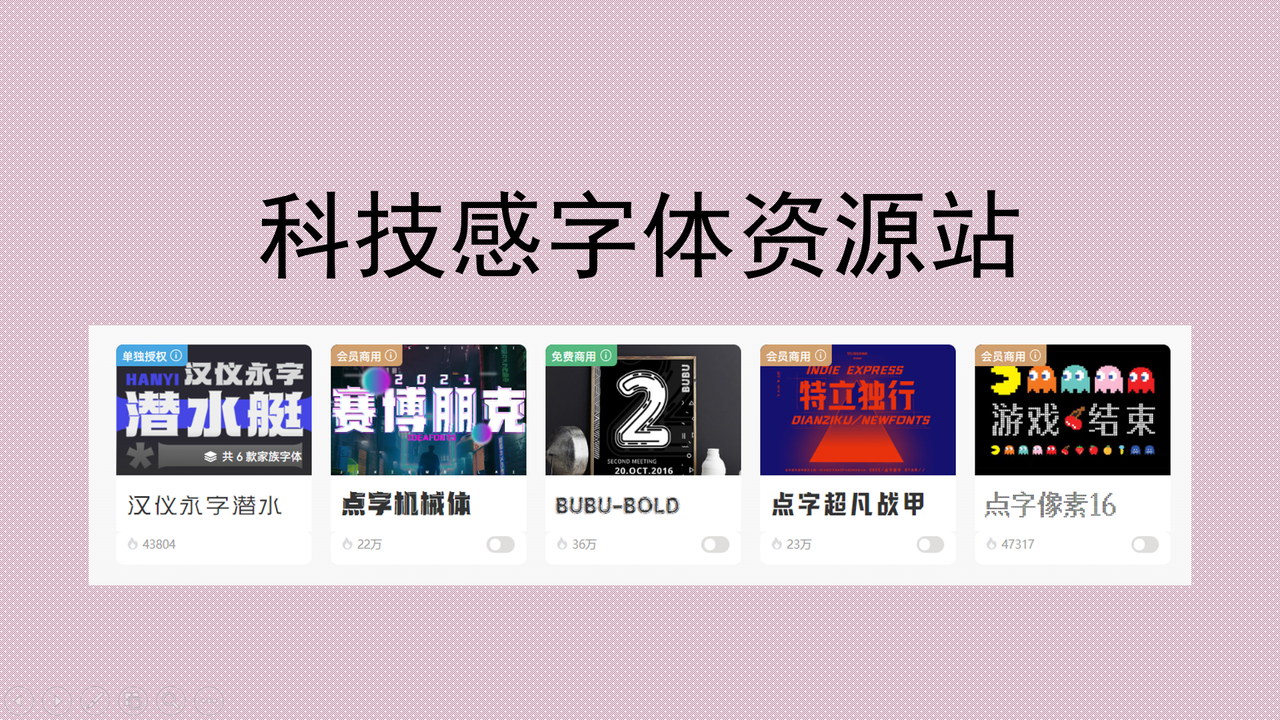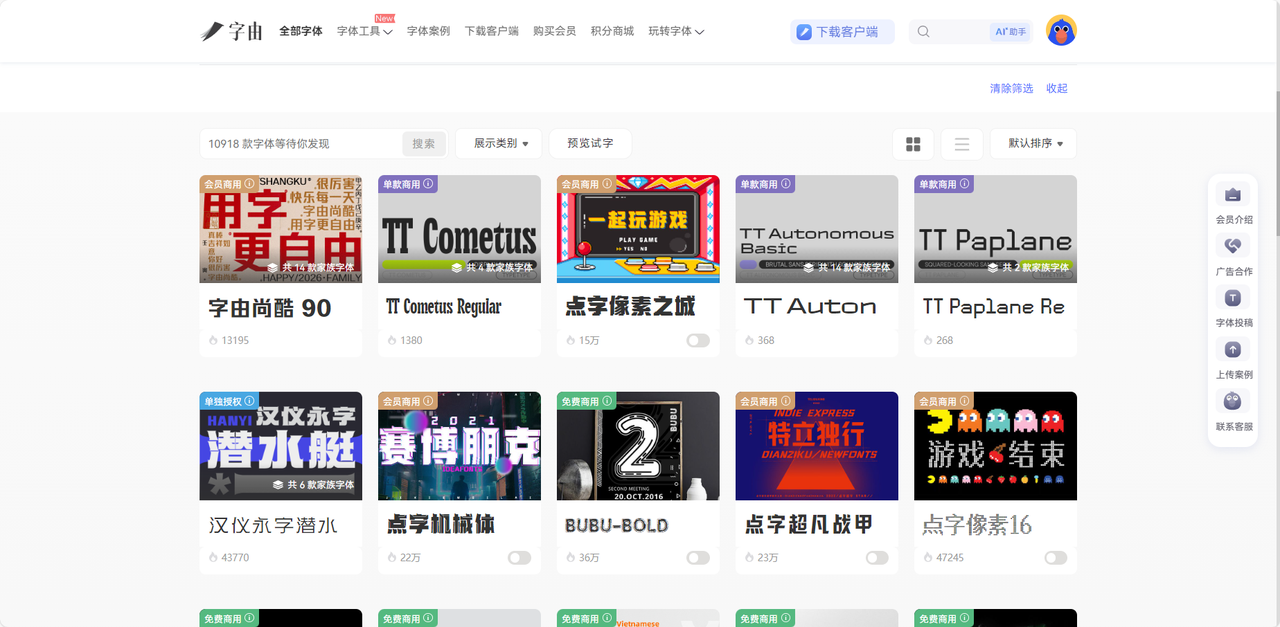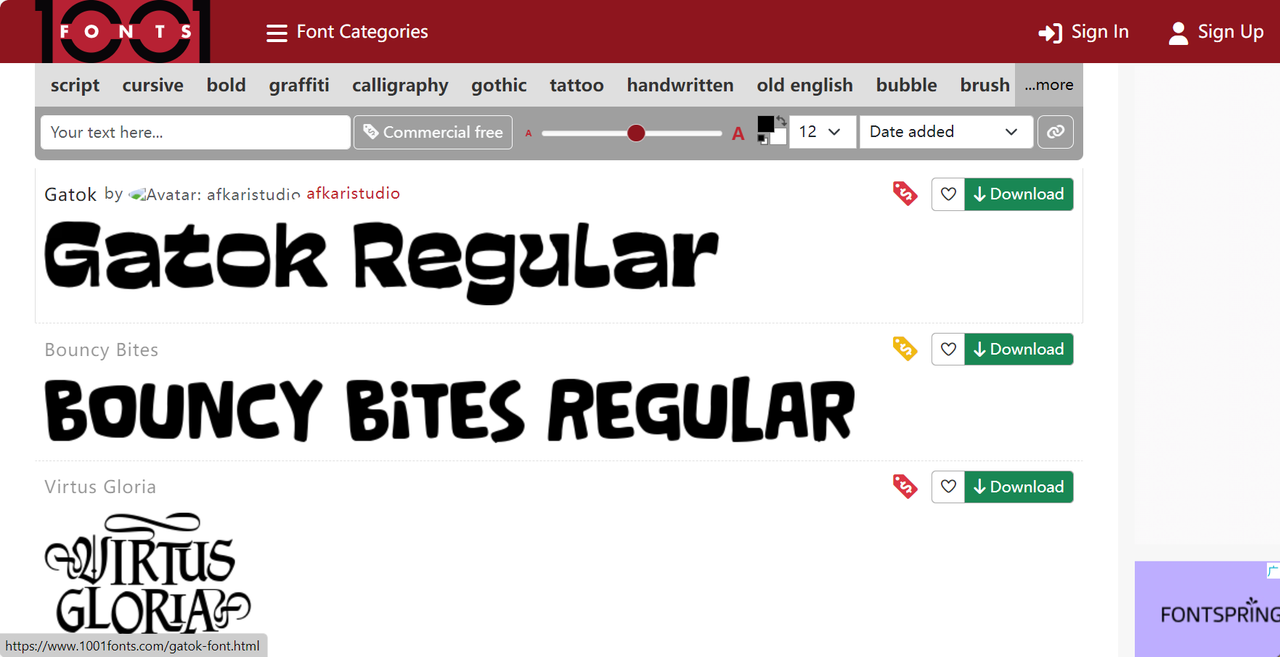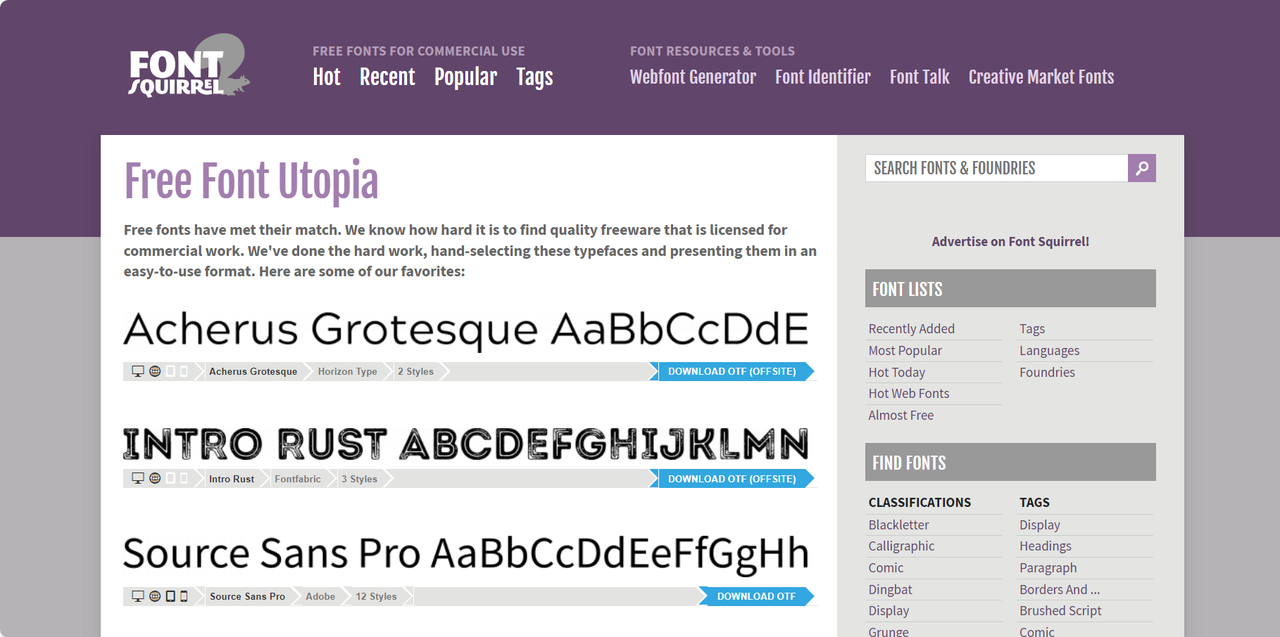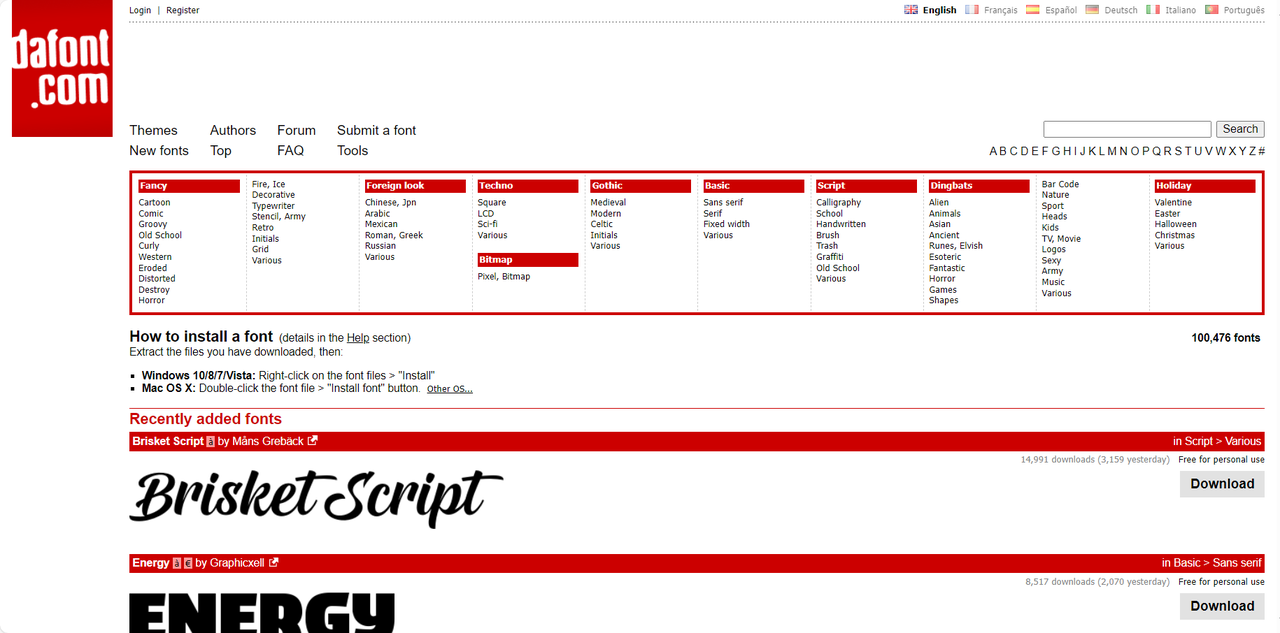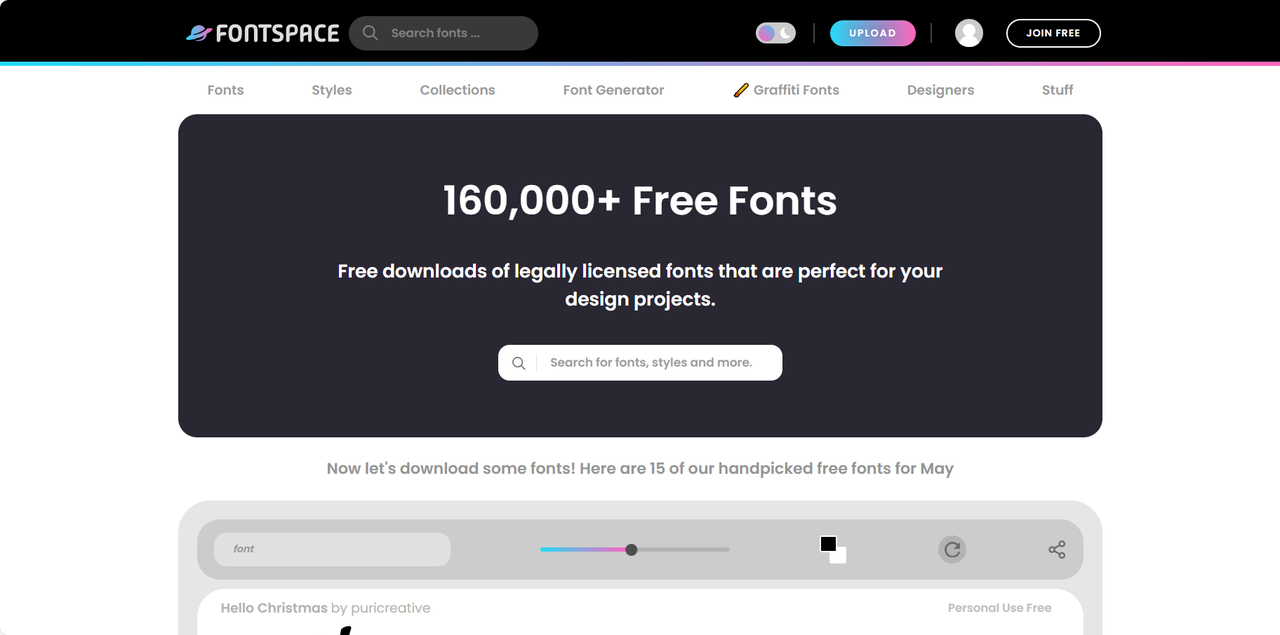
科技感字体怎么获取?推荐几个字体资源站
我们在做科技海报、商业展览或者 UI 界面时,经常需要营造未来感和数字科技感,这种时候选择一款合适的科技感字体就能给作品注入最佳灵魂。通常来说,科技感字体一般是极简几何的线条构图配上赛博朋克的霓虹发光质感,瞬间就能拉到作品的科技浓度。但是寻找到满意的科技感字体经常困扰着大家,要么风格不够丰富、要么无法商用。今天就为大家整理了 5 个科技感字体资源站,从免费商用平台到专业正规字体库,覆盖个人到商用的全场景需求,教你轻松获取适配不同场景的科技感字体。
一、字由
字由想必大家都不陌生,这是国内极具实用性的字体管理工具,内涵上万款不同风格的优质字体,尤其在科技感字体的选择上更是资源丰富,无需跳转多个平台,在这里就能一站式完成筛选、预览以及下载。字由作为上市公司全资品牌,是腾讯、京东、小红书、华为等国内头部大品牌的合作伙伴,字体资源完全值得信赖,且大部分字体都适用于商业场景。
二、1001Fonts
1001Fonts 是一个覆盖范围极其广泛的字体资源站,科技感字体资源适配不同的设计场景,比如网页设计、UI 界面、LOGO 设计、未来风海报等等。用它来获取科技感字体也非常简单,只需要利用平台的场景分类和关键词搜索功能就可以快速完成。如果自带的分类标准不能满足你的要求,用户也可直接在搜索框输入想要的字体类型,提升设计效率。与其他资源站不同的点在于,1001Fonts 的字体质量具备较高的识别度和设计感,且附带不同语言的字符集说明,方便跨语言设计使用。除此之外,它还提供了“Font Preview Tool”功能,用户可以在下载字体之前调整习题大小、字间距、颜色等细节,避免下载后才发现字体呈现效果不适配的问题。
三、Font Squirrel
如果说字由是国内设计师的高效选择,那么 Font Squirrel 就是国外获取开源免费科技感字体的宝藏地,尤其适合预算有限的设计师或学生党。个人认为,这款工具的核心优势就是拥有很多小众但质感出众的字体,且完全开源免费,字体详情页会清晰标注字体的授权协议,大家仔细阅读即可。平台的习题更新速度很快,很多独立设计师也会将自己创作的小众科技感字体上传平台,帮助你轻松打造不撞款且独特的科技感设计!Font Squirrel 支持字体文件下载为 OTF/TTF 格式,部分字体还提供了 Web 字体转换工具,便于用户直接生成适配网页的字体文件,在制作科技风网站的设计师们可以尝试一下。
还有一个想和大家推荐的功能,它还提供了 Font Identifier 工具,设计师可以上传自己喜欢的字体截图,平台会自动识别并推荐相似字体。
四、DaFont
DaFont 是全球知名的免费字体资源平台,拥有海量全球设计师上传的字体,是帮助你打造独特科技风设计的创意宝库。由于它的用户群体覆盖范围广,也造就了平台的多样性和包容性,很多主流平台上找不到的字体,这里都会让你发现惊喜。提起科技感字体,DaFont 上的资源几乎都是独立设计师发原创作品,带着强烈的个人色彩,比如像素风格的复古风字体、机械齿轮风格的工业感字体等。如果你从这里下载科技感字体,能让你的设计会摆脱千篇一律的模板化效果,形成独一无二的视觉风格,给人眼前一亮的感觉。
五、FontSpace
说了这么多字体工具,我们来看看 FontSpace——以社区驱动为核心的字体分享平台。在这里,用户可以对喜欢的字体进行点赞、评论、收藏,也可以关注自己喜欢的设计师,说不定还能交到更多设计师朋友哦,扩展自己的人脉圈,获取到更优质的科技感字体资源。FontSpace 上的科技感字体数量也非常可观,不仅有免费的开源字体,也有设计师分享的付费优质字体,没有灵感的设计师们也可以在这里获取到当下最新潮流趋势,看看别人的设计有助于灵感爆棚哦。最关键的是,FontSpace 除了可以预览字体效果,在字体详情页还可以查看其他设计师的应用案例,也就是俗称的“买家秀”,帮助你来判断字体的实际使用效果。
总而言之,选择合适的科技感字体可以有效提升作品的设计质感。字由的字体资源值得信赖,且适合国内设计师使用;DaFont 和 1001Fonts 有很多小众且富有设计感的创意字体;Font Squirrel 主打提供开源免费的字体资源;FontSpace 给给位设计师们提供了艺术交流的平台,还能获取最新字体潮流。每个平台都有独特的优势,它们已经完全能够满足不同场景、不同预算的科技感字体需求啦,大家可以挑选一个或者几个配合使用。赶紧收藏起来吧!下次想要科技风设计时就可以比别人更快找到心仪字体,打造专业性与未来感兼具一体的作品。